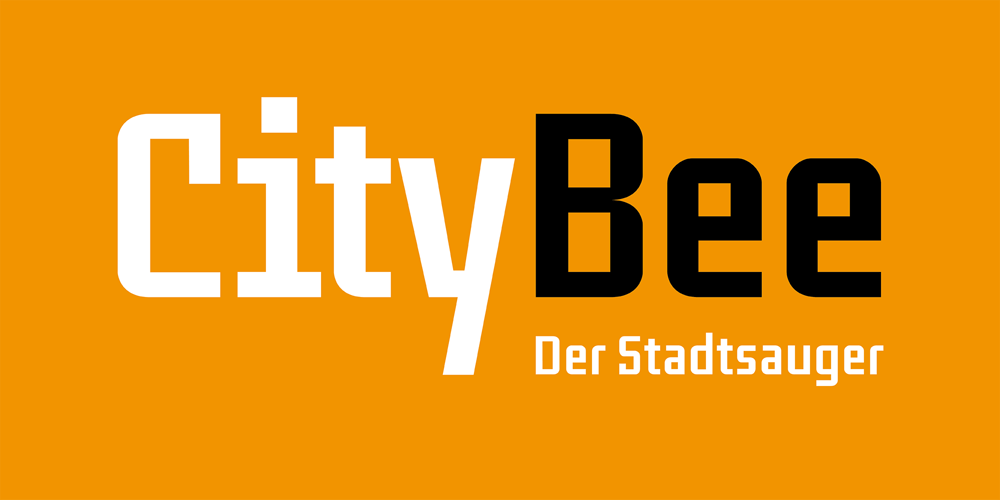
Techtom Font Family was designed by Thomas Matthias Hofmann and published by Typotom Manufaktur Berlin. Techtom contains 1 styles and family package options. Die TechTom ist eine stabile, konstruktive Semi-Serif. Sie eignet sich für Produktgrafiken, technische Texte, zum Plotten, als Plakatschrift oder für Headlines. Wegen ihrer einfachen Formen eignet sie sich besonders für dreidimensionale Anwendungen. Ähnlichkeiten gibt es z.B. zur »City« von Georg Trump.